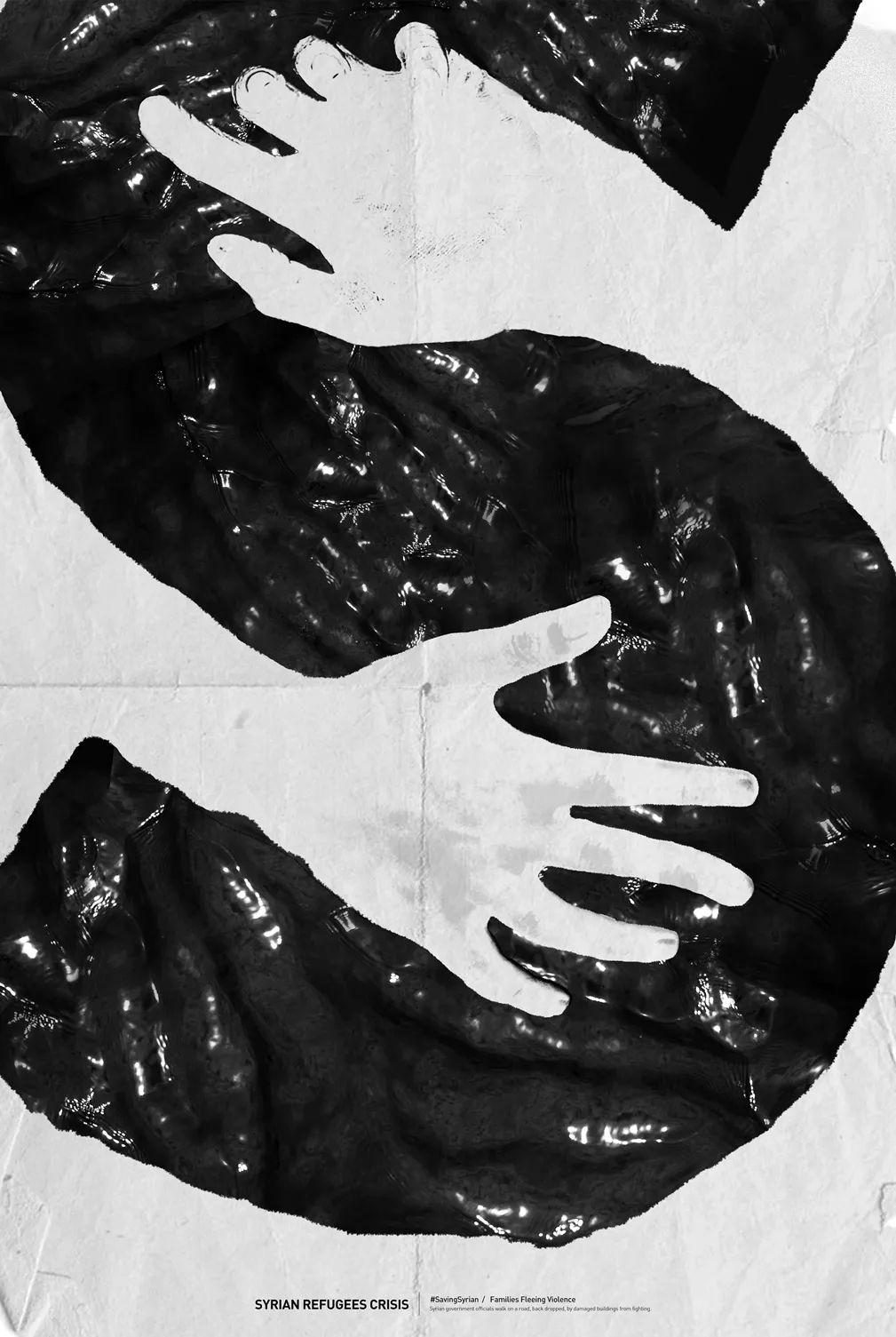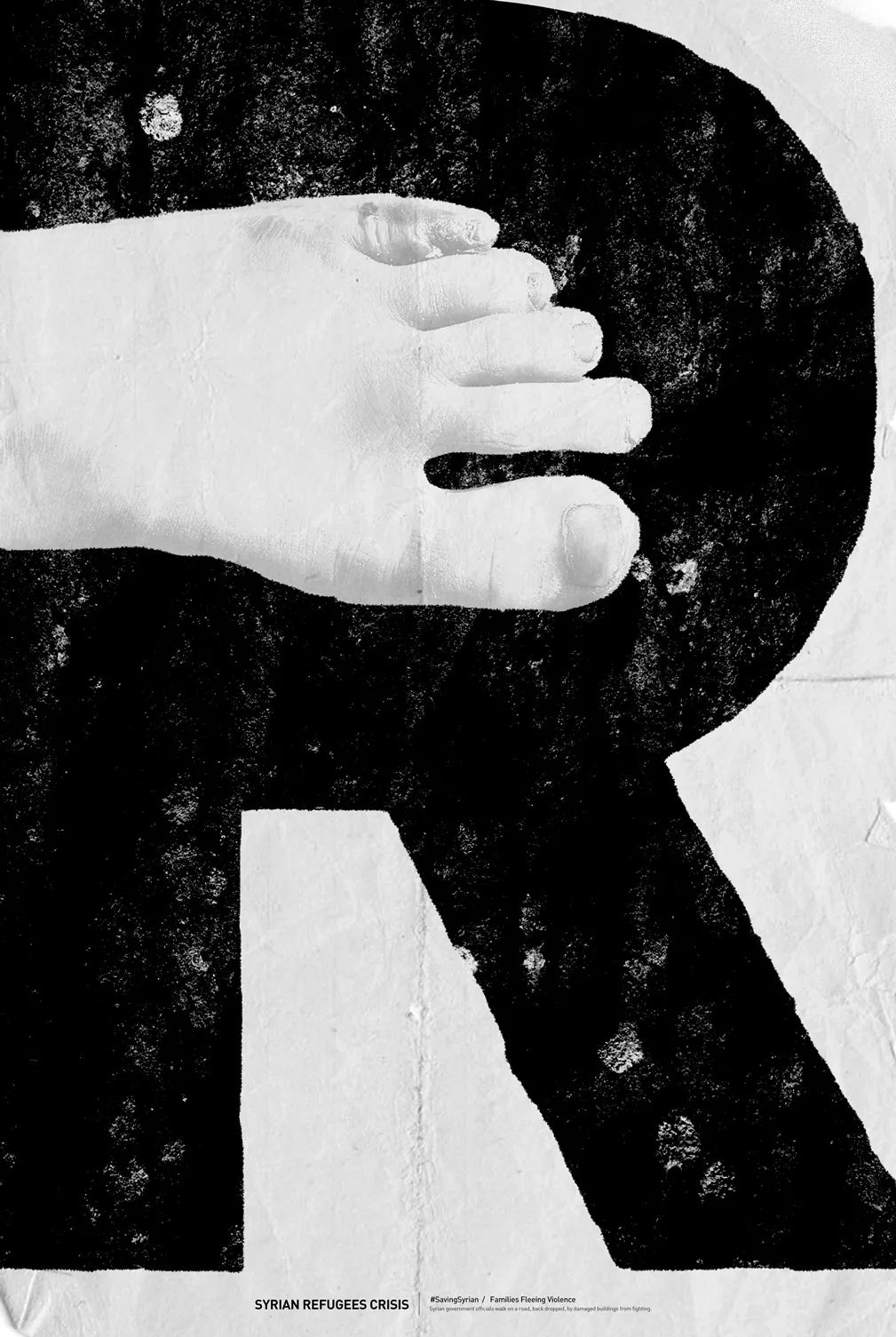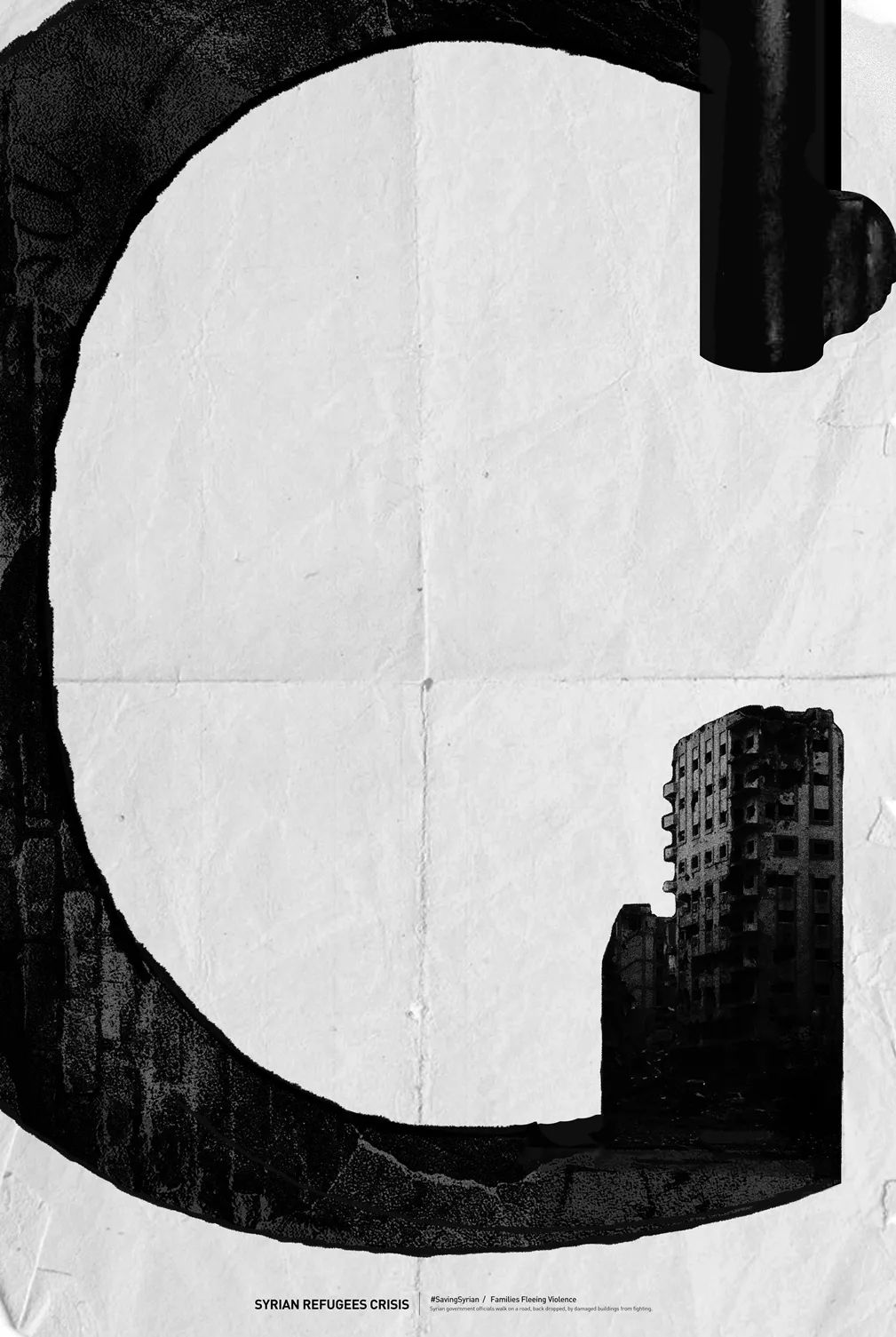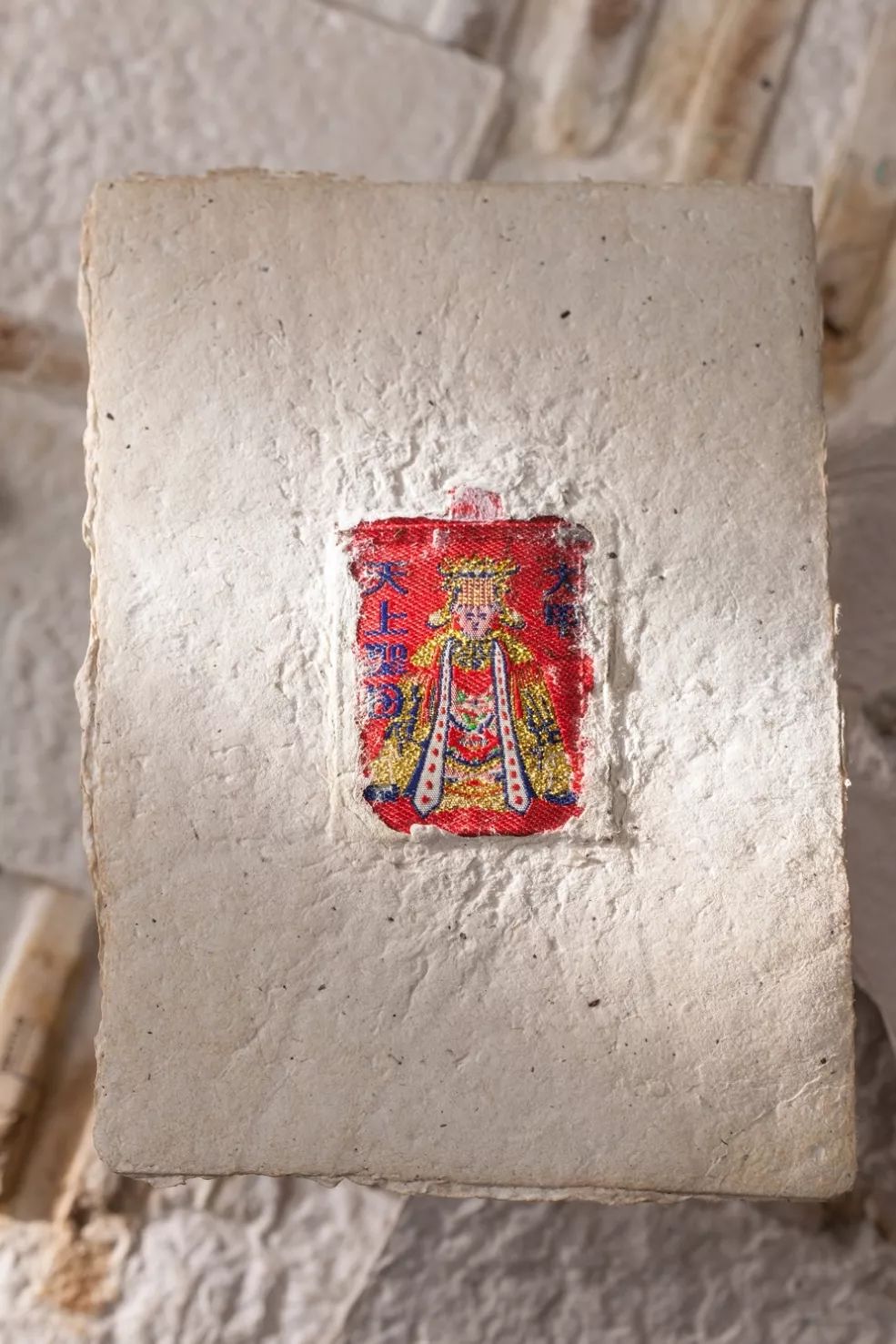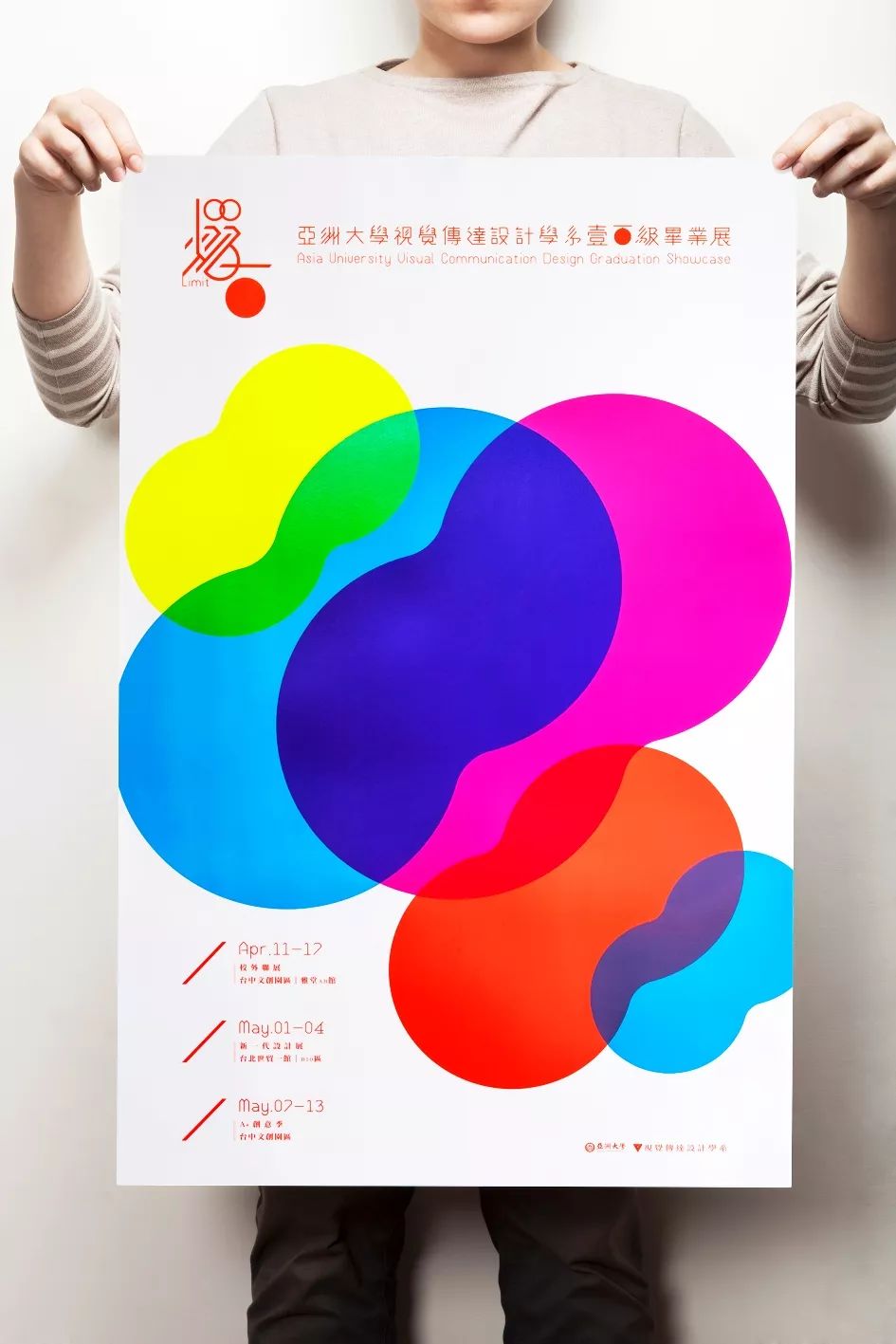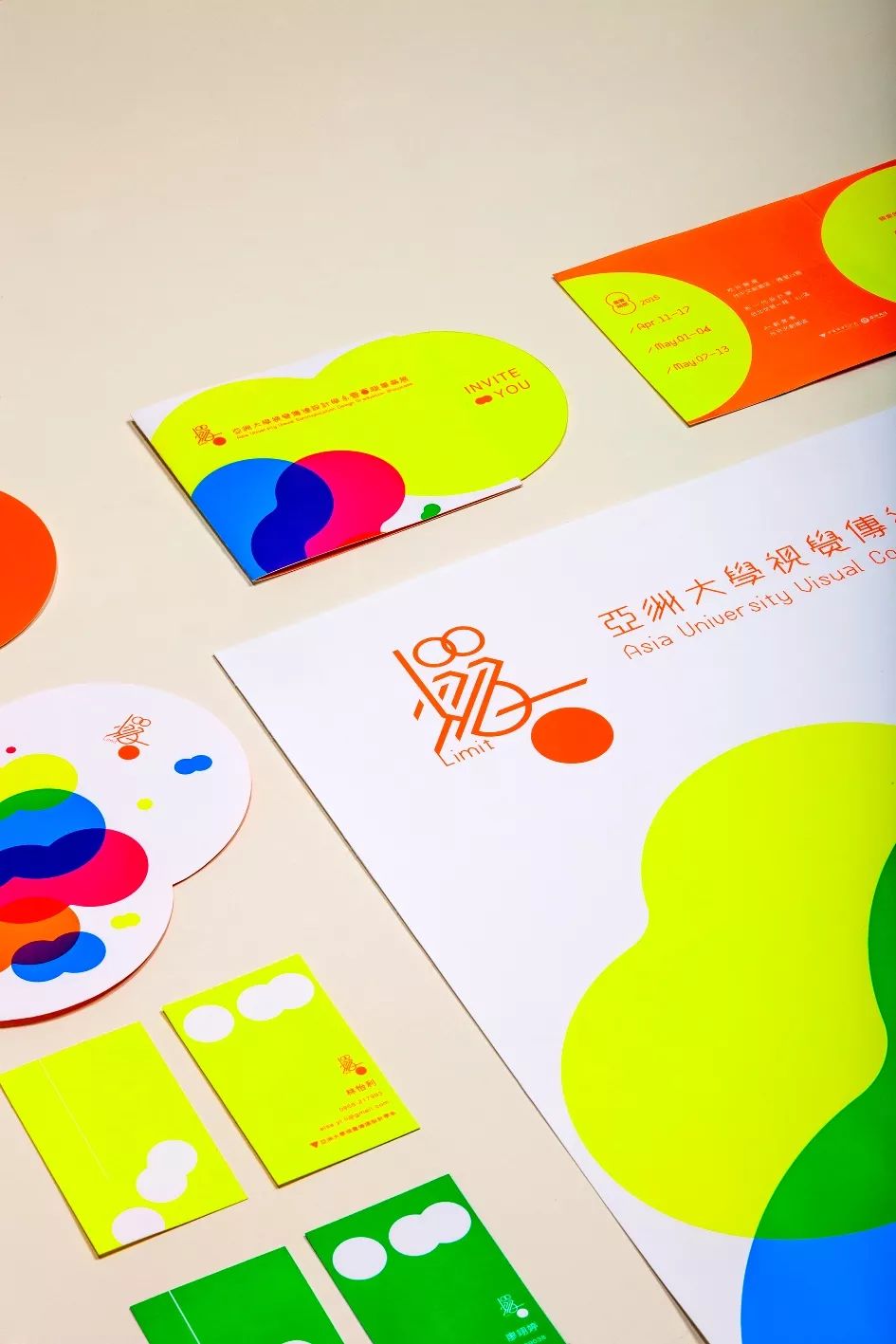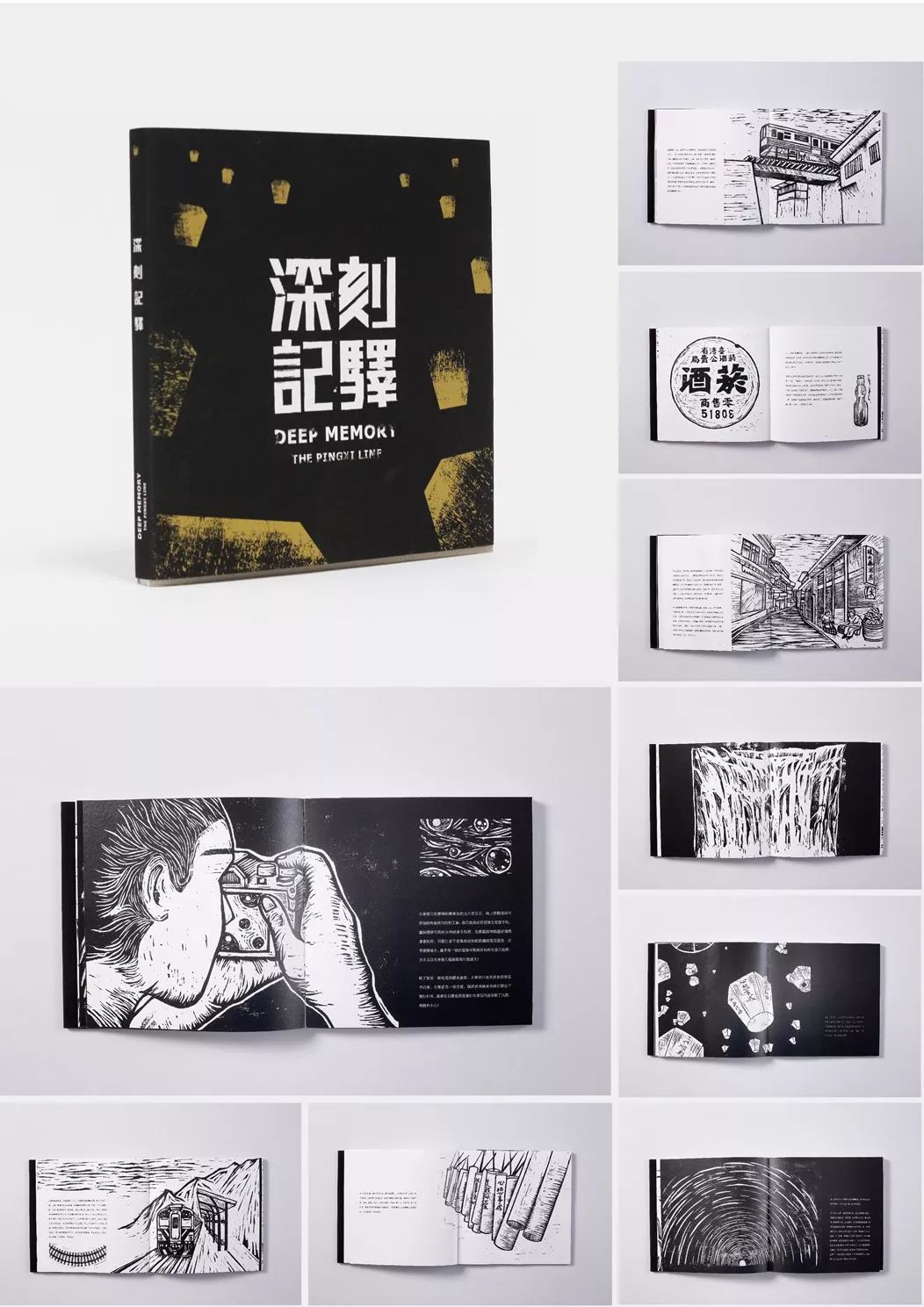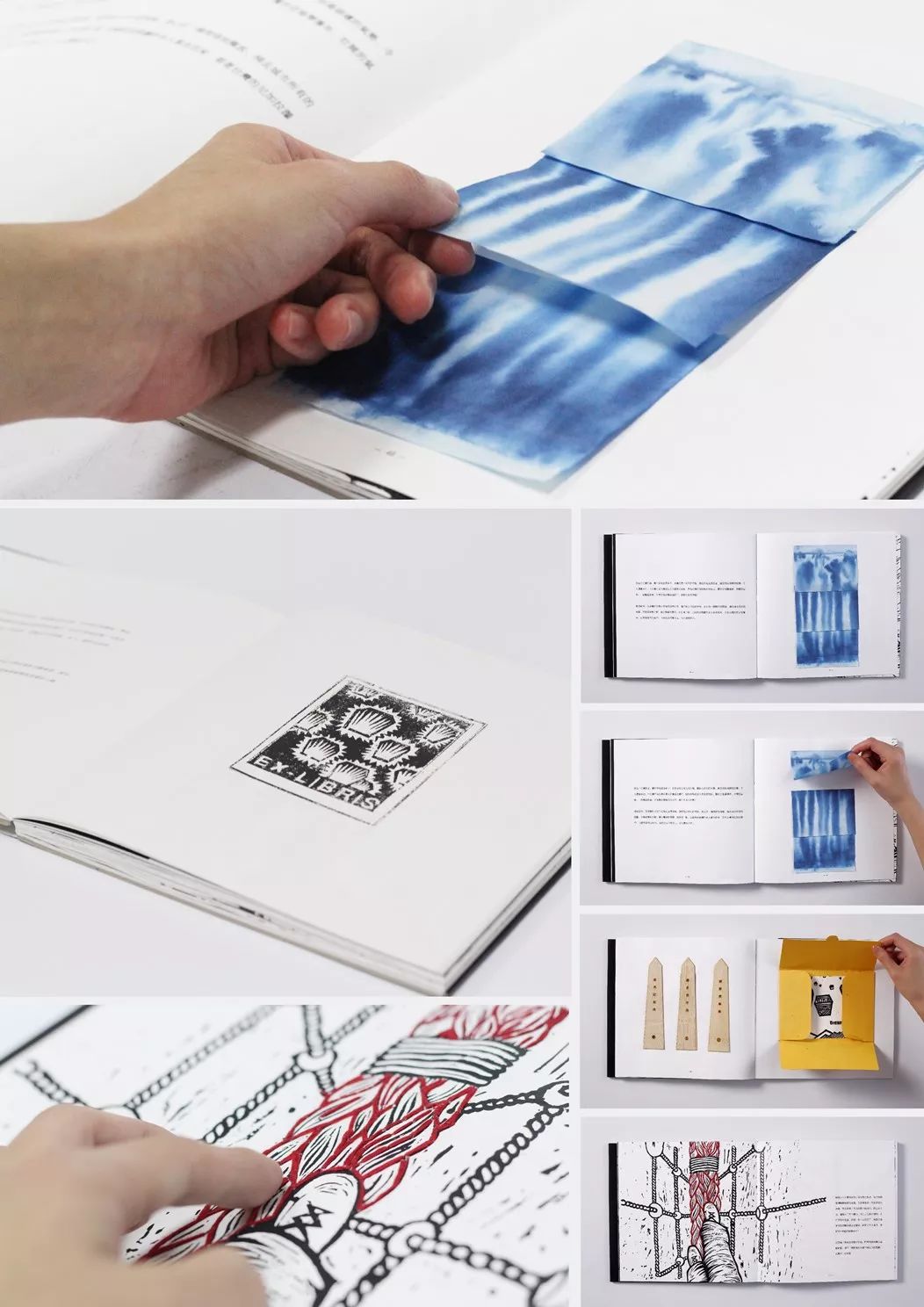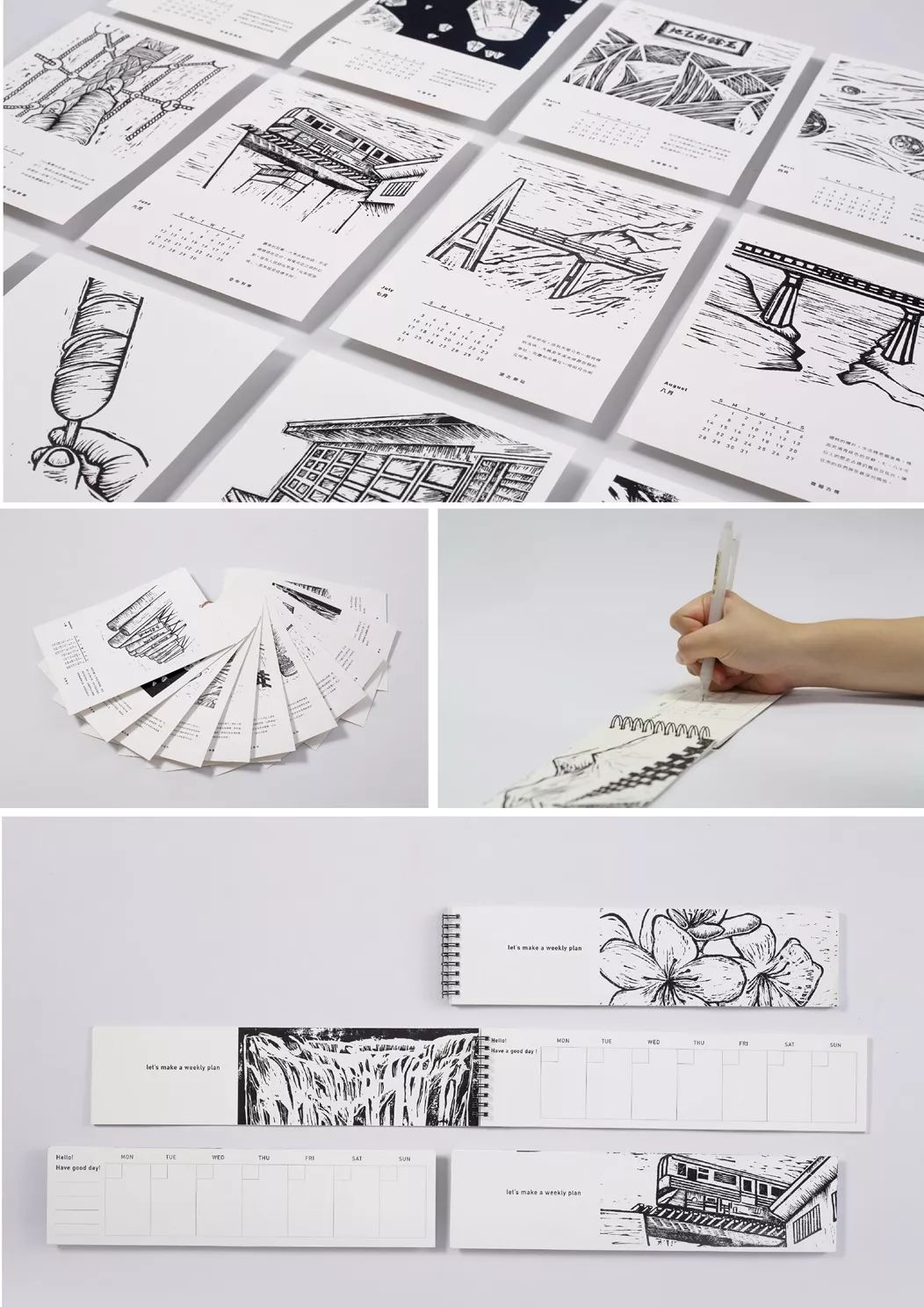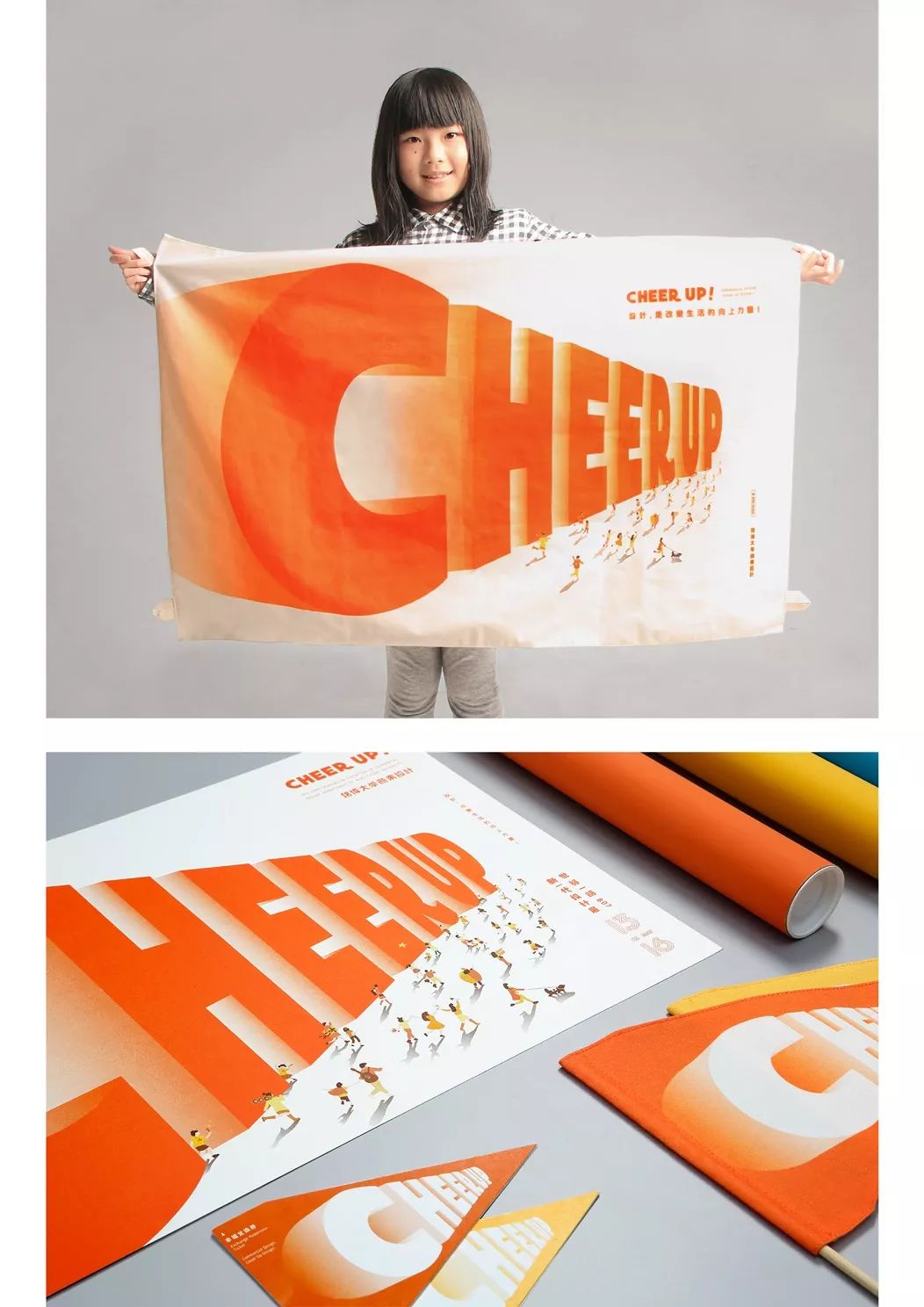
2019台湾金点新秀设计奖——视觉传达类
金点设计奖(Golden Pin Design Award)在1981年创立于台湾,现由台湾创意设计中心(Taiwan Design Center, TDC)办理奖项与策划颁奖典礼及相关活动。2014年起开始走向“全球华人市场最顶尖设计奖项”的新定位,为华人设计产业取得发言权,并自2015年起,金点设计奖品牌针对不同目标族群分设金点设计奖、金点概念设计奖及金点新秀设计奖等三大奖赛,旨在褒扬杰出的创新设计产品与作品。
新一代设计奖成立于2001年,2015年正式转型为国家级的金点新秀设计奖,成为金点品牌奖项的一份子(金点设计奖、金点概念设计奖、金点新秀设计奖),同时为全球规模最大的设计新秀毕业联展盛宴新一代设计展展会中,唯一官方奖项。
视觉传达设计类
视觉传达设计类年度最佳设计奖
山回行
学校名称: 昆山科技大学
科系名称: 视觉传达设计系
设计师: 陈玟利、吴柏翰、叶昕盈、杨程皓、洪家荣、吴承泓
我们想跟大家分享在山里所感受的那些在平常生活中体验不到且特别的经验,透过创作为媒介,进而使观者对山有所认知,并期盼唤醒深藏在灵魂中对大自然的爱与共鸣。
未——主视觉形象
学校名称: 明志科技大学
科系名称: 视觉传达设计系
设计师: 张溥辉
未,如学生的我们,乍看下许多事物混杂不明似一无所有,但也代表着无限可能性。主视觉似面团、云雾感的图形,概念取自还未被制成面包的面团最初(上部)与搓揉后(下部)。在未字上,中空的文字表达「有」与「无」于创作的截然;抽换部分电脑字体笔划,象征透过摸索打破框架的尝试,海报上也借银色油墨特性得移动角度、远近才得以看见文字全貌呼应着主题。白墨覆盖部分图样与资讯,模拟未的迷蒙、暧昧。未,在如隐如现之中。
叙利亚难民危机
学校名称: 醒吾科技大学
科系名称: 商业设计系
设计师: 黄冠纶
重新藉由设计的角度去探讨目前世界上最大的社会议题之一「难民议题」。并以难民当前所遭遇的现况为出发点,呈现以三张为系列性的海报创作。
台湾霓好
学校名称: 辅仁大学
科系名称: 应用美术系
设计师: 林恒逸、陈莲开
生猛张狂,霓虹潮牌。阮将霓虹带入生活,带入潮流。霓虹俗气无看头?阮玩给你看。恁越无要紧,阮越欲做到。天照大地,霓照人间,开眼闭眼,霓伴身边。欲看毋看一句话,尬你挂保证真正有影!台湾霓好,啥款?!
讲干话
学校名称: 树德科技大学
科系名称: 视觉传达设计系
设计师: 蔡伟群、陈怡安、林采玲、许宸玮、郑文雅
这年头,旋转跳跃八卦无极限,流言是非白眼翻天狗跳鸡飞,什么人讲什么话,台湾人讲台湾话,SHE说全世界都在讲中国话,无理的人听不懂人话,新时代潮人流行讲干话。
视觉传达设计类获奖作品
狮纸
学校名称: 铭传大学
科系名称: 商业设计系
设计师: 尤心慈、陈俞君、李东陵、谢其晖
「狮纸」将狮艺与纸艺结合,设计出华人文化特有的创新型纸艺舞狮。受到立体折纸线、面、体造型启发,利用一张张纸即可组成狮头,以最纯净简单的白模体现舞狮工艺之美。
一鸣惊人
学校名称: 树德科技大学
科系名称: 视觉传达设计系
设计师: 李昱志、黄贵城、蔡郁平、丁嘉惠、曾巧茹
本创作转化传统竹蝉童玩,结合ic晶片与触动装置,设计九只台湾特有种蝉的电子玩具,并将蝉的声音抽象视觉化在玩具涂装上,配合包装与书籍的延伸,期许达到寓教于乐目的。
午星级学堂
学校名称: 辅仁大学
科系名称: 应用美术学系
设计师: 黄宇璇、李昱颍、于思文
文武妙妙庙
学校名称: 朝阳科技大学
科系名称: 视觉传达设计系
设计师: 吕俊毅、陈韦儒、黄靖雯
日月潭文武庙重建至今逢50周年,借此设计以简明图文了解参拜流程,欣赏建筑艺术,体会其中的文化内涵。并采龙鳞装帧,由外而内随翻阅而改变的图像带领读者更深入探索。
十八辣醒
学校名称: 中国科技大学
科系名称: 视觉传达设计系
设计师: 杨彦伦、李宗翰、庄庭瑄、陈美存、郭博竣
本设计以「辣味泡面」作为主题, 选定猪、牛、海鲜三种大众口味, 以十八层地狱带来前所未有的感受, 以图像创意呈现极限味觉的幽默设计, 创造消费者对品牌的惊奇。
一件事
学校名称: 明志科技大学
科系名称: 视觉传达设计系
设计师: 王奕、叶佳怡、邱靖雅
「多数人把坏事看得仔细也记得透彻,只因他们看见的好并不够好」一天不过24小时,我们却总让那些媒体的浮夸虚假占去大半;渐渐地我们也成了其中的恶趣味。倘若这短暂的一天总是好事相报,那么是否也会变得趣味多?
合
学校名称: 实践大学
科系名称: 工业产品设计学系
设计师: 彭慧然
透过磁粉的聚合与form来表达主视觉的概念,因新一代就是一个不断合的平台——业界与学界、学生之间、发想概念时,点子与点子之间的联结、去芜存菁等。其中放了两段Jobs的话,与要从设计系毕业的同窗们共勉之。
净爱高山
校名称: 岭东科技大学
科系名称: 视觉传达设计系
设计师: 林佩萱、罗敬邦、张雅雯、黄觉深
从初踏雪山的美丽,到见证玉山的壮丽;从看到土地真貌的心疼,到抚平山林伤口的脆弱, 我们将号召众人净山的过程以影像及文字纪录编辑成书,读者可透过书本的影像及文字一同感受台湾高山的壮丽与哀愁,更看见净山者们的精神与希望。我们也将捡拾下山的垃圾经清理后与纸浆结合成手感明信片,透过明信片传递环保的省思,重新定义并赋予它全新的价值。我们传递着一个精神——净爱高山。从净山开始,从心里出发,慢慢发扬光大。净爱高山,也净爱高山。
台湾妖兽GOOD – 民俗妖怪公仔
学校名称: 台南应用科技大学
科系名称: 视觉传达设计系
设计师: 刘忝桂、黄宜瀞、蔡文雯、谭惠文、赵子萱、谢佳悦
鉴于民俗传统没落,本团队以台湾民间传说为主,截取各时期鬼怪故事并附予角色新造型,以其设计出台湾特有妖怪公仔。本作依故事情境带入趣味动态表情,呈现诡异但不失欢乐气氛,希望让观者对台湾文化有更进步的认识。
熠百
学校名称: 亚洲大学
科系名称: 视觉传达设计系
设计师: 王怡苹、蔡嫚嫔、廖翊婷、张雅婷、谢孟轩、林怡利
起始的圆,澄净又充满可能性,拥着热忱不断向前,无畏无惧,结合创意凝成露珠,在未来流光溢彩,迎接极限。
台湾之光
学校名称: 辅仁大学
科系名称: 应用美术系
设计师: 赖加瑜、潘薏心、蔡名扬、江政儒
你可曾注意过街道旁的路灯都长得不一样呢?它们为了照亮台湾而默默地伫立着。为了记录全台各地特色路灯,我们实地走访了台湾六十个乡镇,并搭配当地景点绘制成台湾路灯手札,提醒大家抬头看看这些被忽略的台湾之光。
字新颖
学校名称: 私立复兴高级商工职业学校
科系名称: 广告设计科
设计师: 陈丽儿、卢昕妤、庄惟中、庄晨、吴亚芸、蔡蜜平、陈伽蓁、何孟娴、黄云镱、高侑琳
一般认知的学习就是翻开书本,将理论塞进脑袋里,但这样的学习方式不仅无趣,学习成效也未必良好,于是我们提出构想,将汉字与生活中常用到的事物结合,透过使用与欣赏及趣味的方式接触汉字达到更好的学习。
深刻记驿
学校名称: 亚洲大学
科系名称: 视觉传达设计学系
设计师: 黄郁晴、陈怡贞、张丞胜、卢姿妤
曾经好友一同出游到平溪,赫然发现平溪线历史悠久,亦最美丽的支线,保有丰富的历史、人文、自然之美,希望可以记录当下这份感动分享给更多人,我们选用木刻版画的方式呈现,呼应产煤挖矿的过程,记录平溪深刻记驿。
CHEER UP!
学校名称: 铭传大学
科系名称: 商业设计学系
设计师: 卢欣琪、王学琪、王用宾、吴秉诚、欧阳竞康
设计,是改变生活的向上力量。从个人到大众,从快乐到幸福,这是设计向上超越、鼓舞生活的旅程。CHEER UP不仅作为主视觉,更将设计带入偏乡小学,让新一代牵手下一代共同踏上创意大道。向上力量,幸福本源。
边缘色– 台湾石头制粉彩
学校名称: 铭传大学
科系名称: 商业设计学系
设计师: 张妍缇、黄于珊、陈其安、陈欣婷
以大地色为出发点,我们收集台湾各处的石头,研磨加工制成粉彩,再造石头的价值。视觉上运用石头轮廓及边缘的发光来呈现平常不被注意却独特的石头,以蓝色为标准色则是希望透过明亮的色光衬托出沉稳而美丽的大地色。
墨生气
校名称: 国立台湾艺术大学
科系名称: 视觉传达设计学系
设计师: 陈正心、潘加哲
拦轿体字体家族
学校名称: 国立台湾艺术大学
科系名称: 视觉传达设计学系
设计师: 林品君、陈彦慈、陈彦宏、陈亚爵
拦轿原意为大甲妈神轿所经路边摆神案祭拜妈祖。取名为拦轿希望把历史文化拦下来,如信徒将妈祖的轿子拦下来祈福,在当代结合文字设计记录下古今汗青。以大甲妈祖为特色发展出三种字体,为灯笼体/贞节体/书刻体。
不是美术系
学校名称: 辅仁大学
科系名称: 应用美术系
设计师: 郭展源、陈舒珊、廖怡涵
多了不那么拘束的活泼,和看似没有条理的叛逆,鲜明的独立在其他认知之外,名字里有着美术系的痕迹,却完全不是那么一回事——应用美术系。在美术与设计的交集中找到喷漆,同一种媒介却能呈现出不同的个性。
起步走
学校名称: 岭东科技大学
科系名称: 视觉传达设计系
设计师: 梁宗玮、李佑瑄、陈颖蓉、廖郡亭、李品桦、郑孟佳
马术治疗是带给身障孩童快乐的物理治疗。透过跨界合作以马匹行走节奏创作音乐突显治疗特色,以孩童的角度创作组合式教具并编写刊物。藉由设计拉近马术治疗与大众的距离!
100%纯污水制冰所
学校名称: 国立台湾艺术大学
科系名称: 视觉传达设计学系
设计师: 洪亦辰、郭怡慧、郑毓迪
你是否正视过纯净的重要?用受污染的水源制成冰品,透过吸引人的冰棒包装,让人产生想拿起来的欲望,拆开后发现冰棒的构成源于污染的水及恶心的内容物,透过冲击感,传达无污染水对人类的重要性,达到让人省思的目的。
社子岛里长竞选计画
学校名称: 辅仁大学
科系名称: 应用美术系
设计师: 李得嫕、谢杰耘、麦晓文
今年21岁的我,住在禁建四十七年发展停滞的社子岛。看着家园从未被重视并改善,我想要化身为社子岛里长候选人,利用设计的力量,提出符合居民想法的施政白皮书与未来蓝图,期许让更多人认识社子岛并关注其议题。
塑缚
学校名称: 国立台湾艺术大学
科系名称: 视觉传达设计系
设计师: 许馨尹、许峰铭、林孟萱
以被塑胶「束缚」的意象讲述宝特瓶污染的环保海报设计。将生活中使用的宝特瓶解构重组,以「缠绕、捆绑与束缚」的概念,来讲述大自然的反噬,重新演绎宝特瓶与人的关系。
尔玉
学校名称: 铭传大学
科系名称: 商业设计系
设计师: 王舒睿、曾琬庭、马佩秀、吴优
尔玉体(Eurus)是一套以「秦篆」为骨骼、「篆刻」为蓝本,所发展出来的英文字型,专门用来呈现古诗文英译版本的视觉编排,借以让更多人领略文字灵韵和古典文化之美。
台湾工务所
学校名称: 树德科技大学
科系名称: 视觉传达设计系
设计师: 周丽婷、黄涵翌、王家仪、林宣妤、许庭凤、汤齐恩
八零年代,台湾以手工具王国著称。制作一系列的手工具包装,并依工具特性结合台湾重大建设与产业为视觉表现,而包装概念则以工具使用时的动作作为方便拆解的一次性包装。
鸟屿风吹
学校名称: 树德科技大学
科系名称: 视觉传达设计系
设计师: 罗亦轩、郑景仁、陈芫茹、陈姿羽、黄音齐、黄筱茜
台湾是拥有丰富鸟类的岛屿,因环境破坏,许多鸟类濒临绝种,故以风筝为设计载体,介绍濒危的台湾保育鸟类,将其翱翔天际,重现百鸟飞翔之情境,希望唤起人们环境保育的意识。